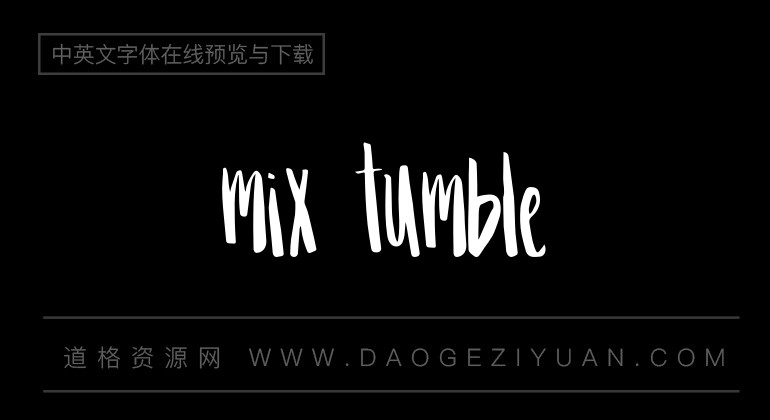
Mix Tumble
Mix Tumble 字体是一种现代风格的手写字体,具有流畅的线条和独特的形状。它的设计灵感来自于手写草稿的感觉,字母的形状看起来像是随意拼凑而成,但整体却非常和谐。 Mix Tumble 字体包括大小写字母、数字、标点符号和一些特殊字符,适合用于各种设计项目,如海报、包装、品牌标识等。使用 Mix Tumble 字体可以给你的作品增添一份现代、有趣的感觉,吸引观众的眼球。 此外,Mix Tumble 字体还有不同的变体,例如 Mix Tumble Rough 和 Mix Tumble Outline,可以为你的设计增加更多的选择和变化。
Mix Tumble是一款非常不错的手写艺术字体,具有很好的视觉感,适合于文化类的宣传设计、商业类品牌的广告和产品包装设计以及个性化文字排版等较多场景。